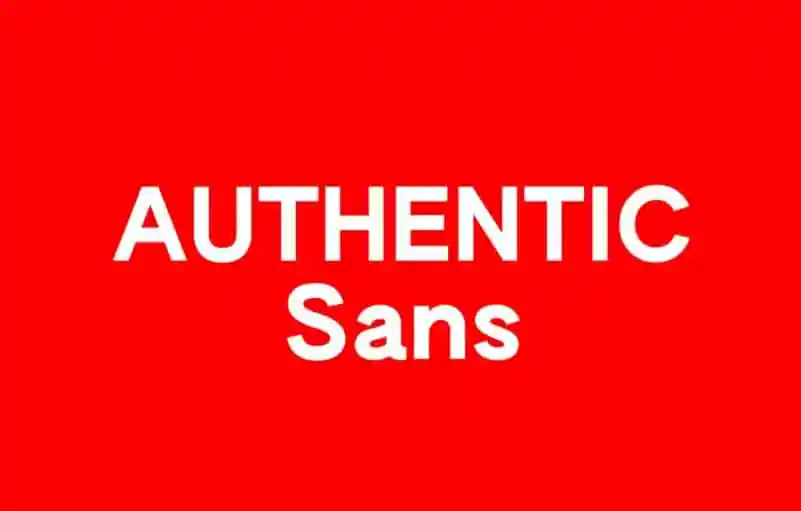
A Authentic Font Family é uma fonte sans serif que traz consigo uma sensação casual e limpa sem perder a versatilidade necessária para qualquer projeto visual. Com 8 diferentes estilos disponíveis, esta família de letras é perfeita para criar designs em todas as escalas, seja grande ou pequeno. É um design elegante e versátil que enfatiza a criatividade e a individualidade através das linhas retas e de design alongado. Suas letras maiúsculas poderosas e fortes, combinadas com linhas finas e abertas nas minúsculas, tornam esta família fonte uma escolha eficaz em diversos campos de projeto. Seja para projetos de marca, designs para casa, embalagens de produtos ou cabeçalhos de revistas, ou mesmo como um overlay estiloso sobre qualquer imagem de fundo, a Authentic Font Family é uma opção excelente e versátil.